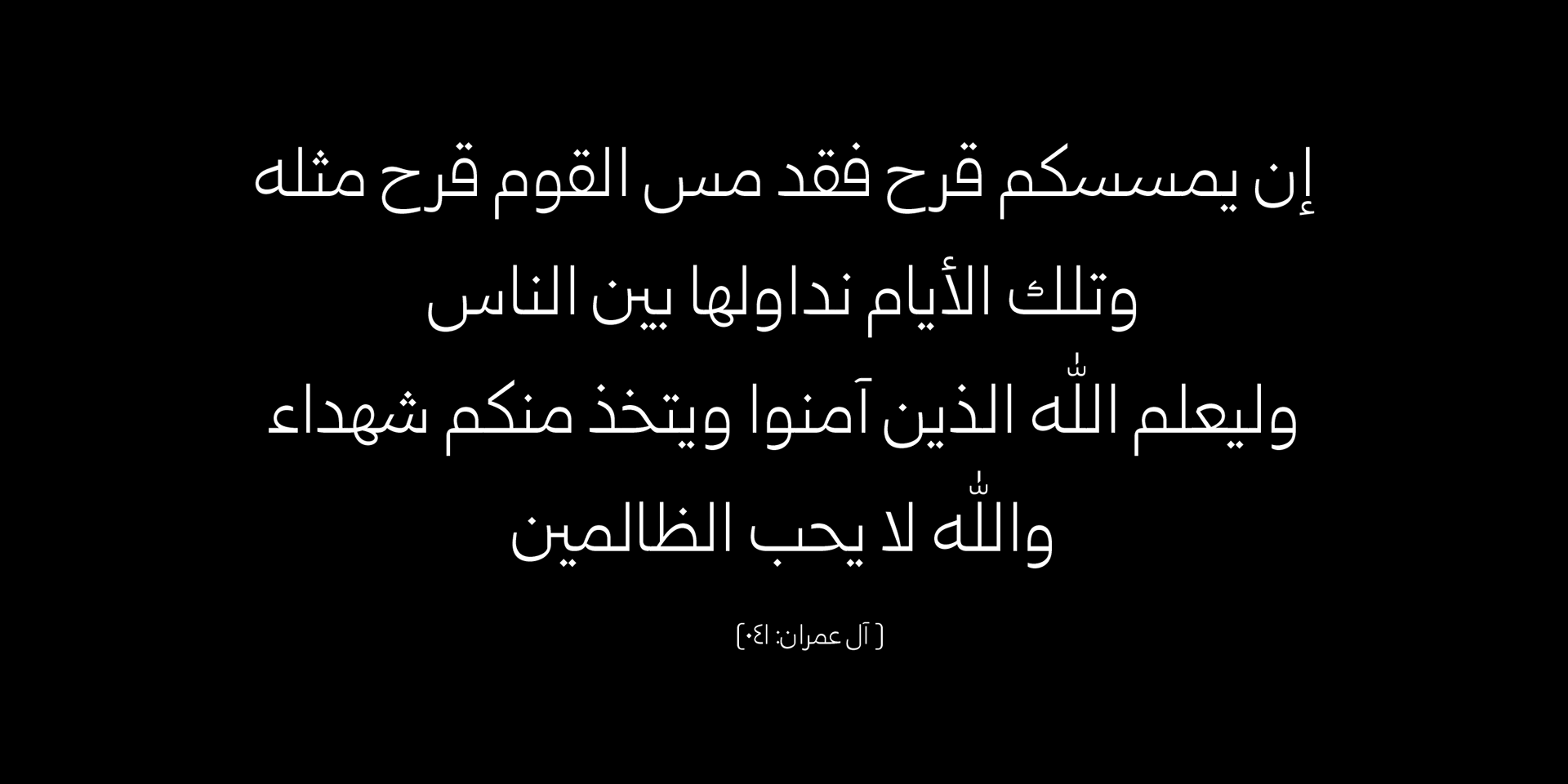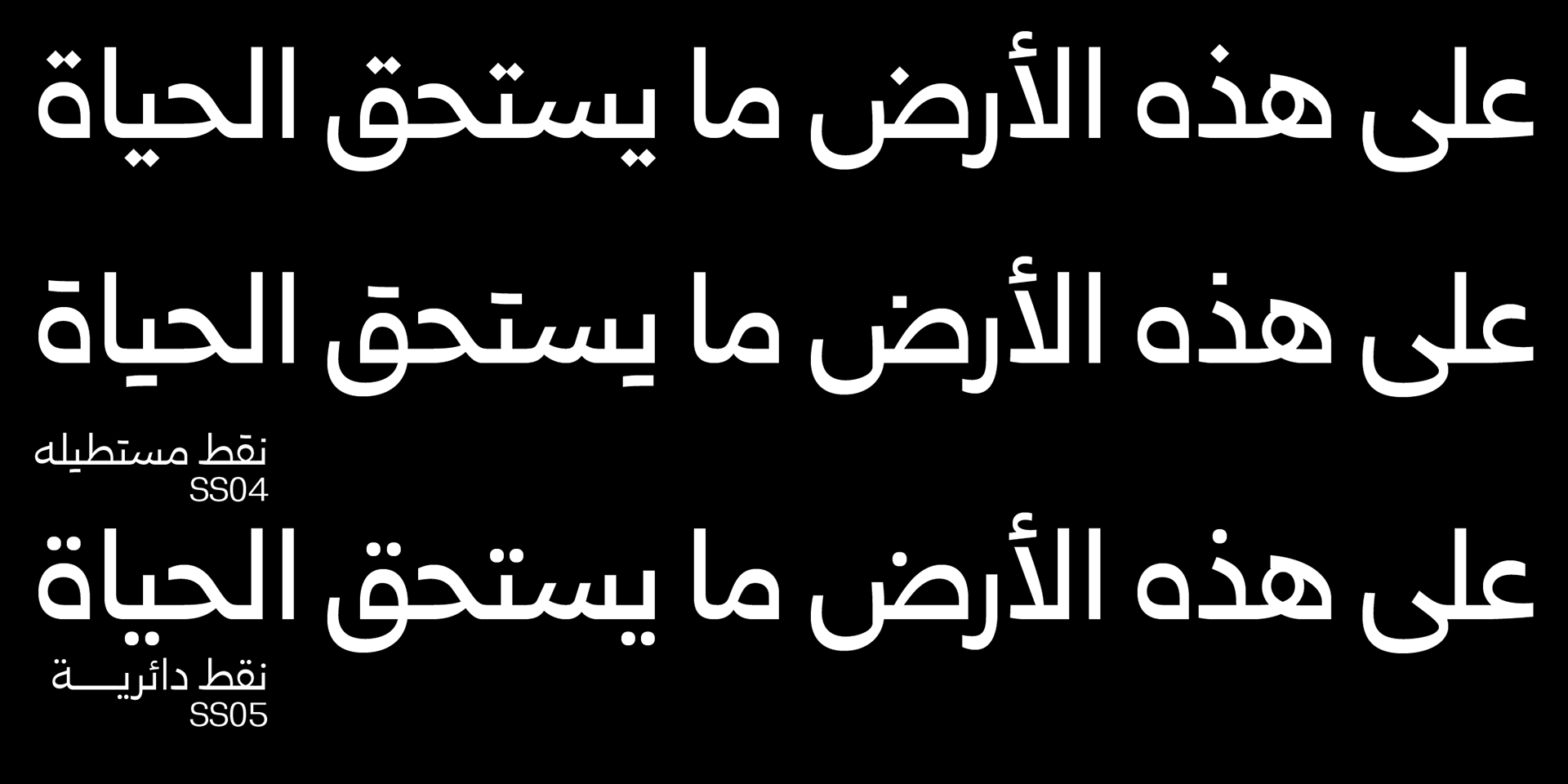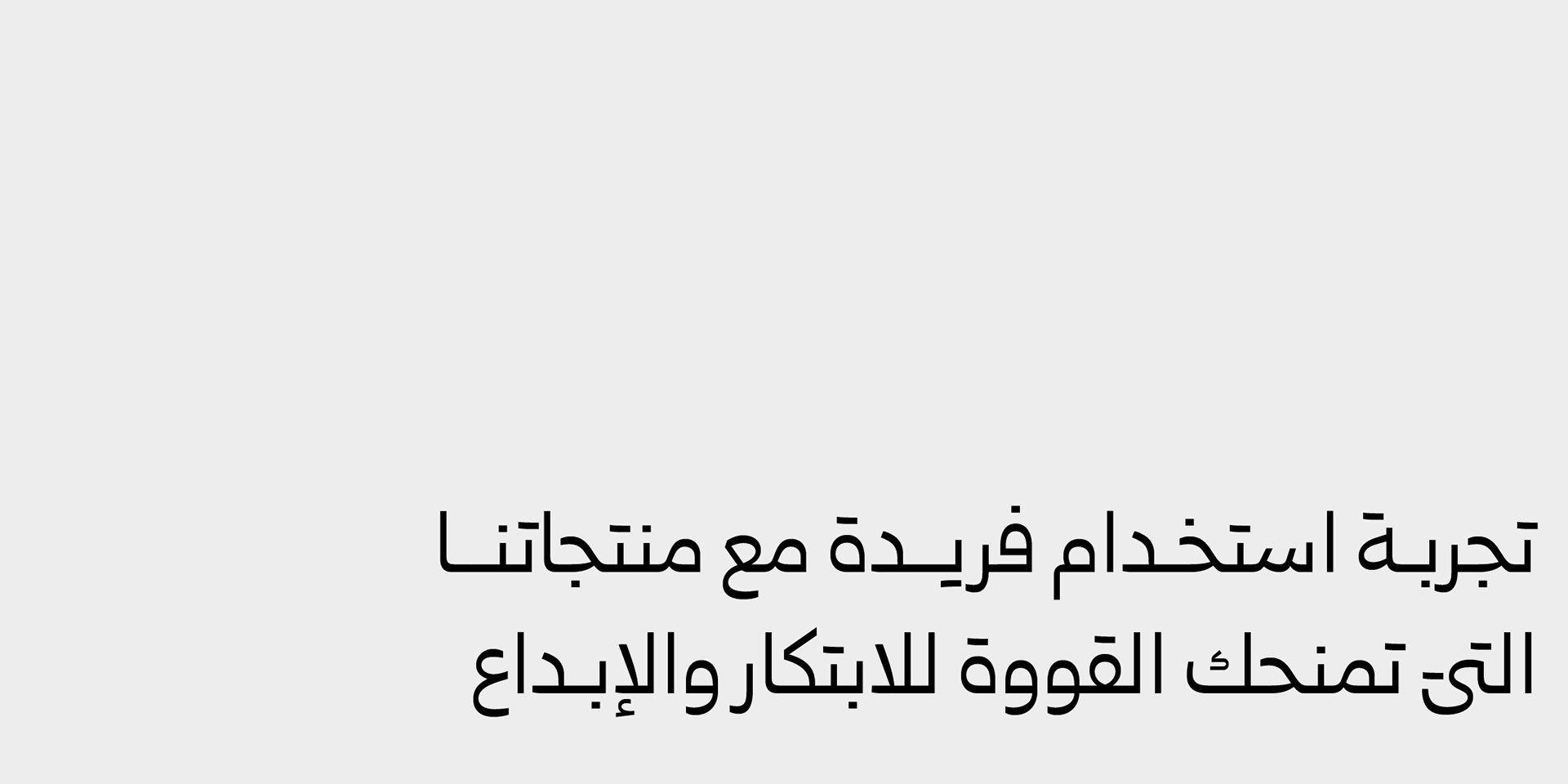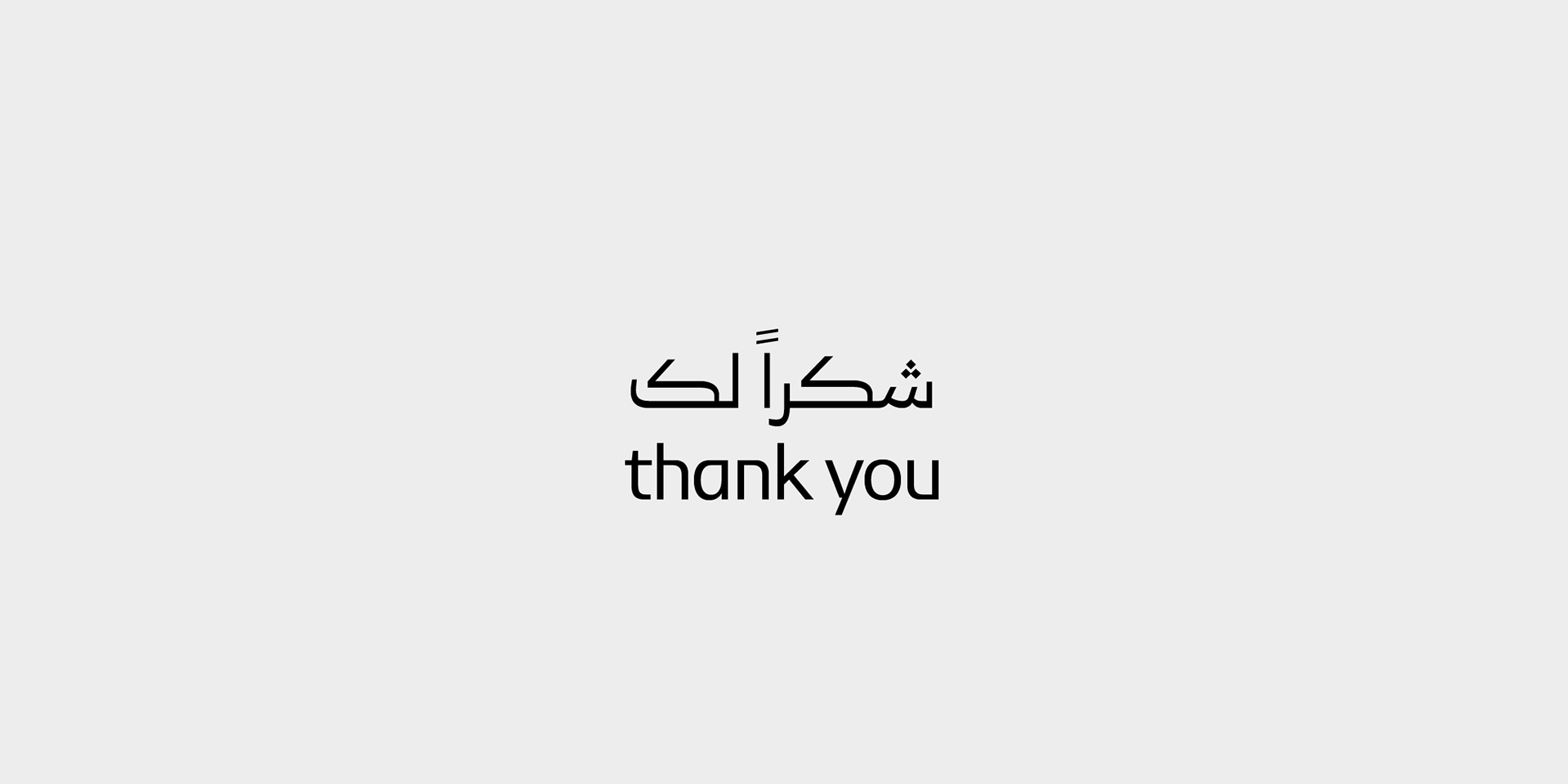
خط غروب العربي الطباعي خط نسخ - Ghroob Arabic typeface
هو خط عربي فريد ومتميز، مستوحى من خط النسخ،يتميز بتصميم بسيط وانيق. والعديد من اوبن تايب من حروف مركبة و مرسلة ونقاط بديلة. يمكن استخدامه في تصميم الجرافيك، والكتابة المطبوعة، والويب، والتطبيقات المحمولة.
It is a unique and distinctive Arabic font, inspired by the Naskh script. It features a simple and elegant design, and includes many OpenType ligatures, Swash letters, and alternative dots. It can be used in graphic design, print writing, web, and mobile applications